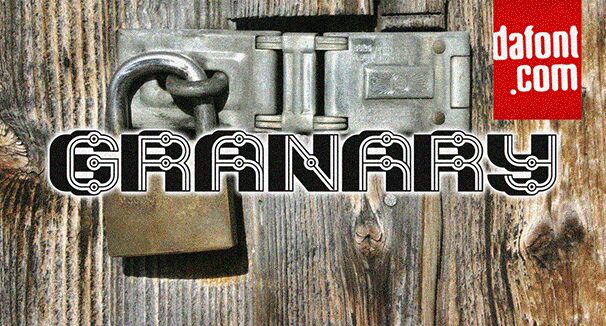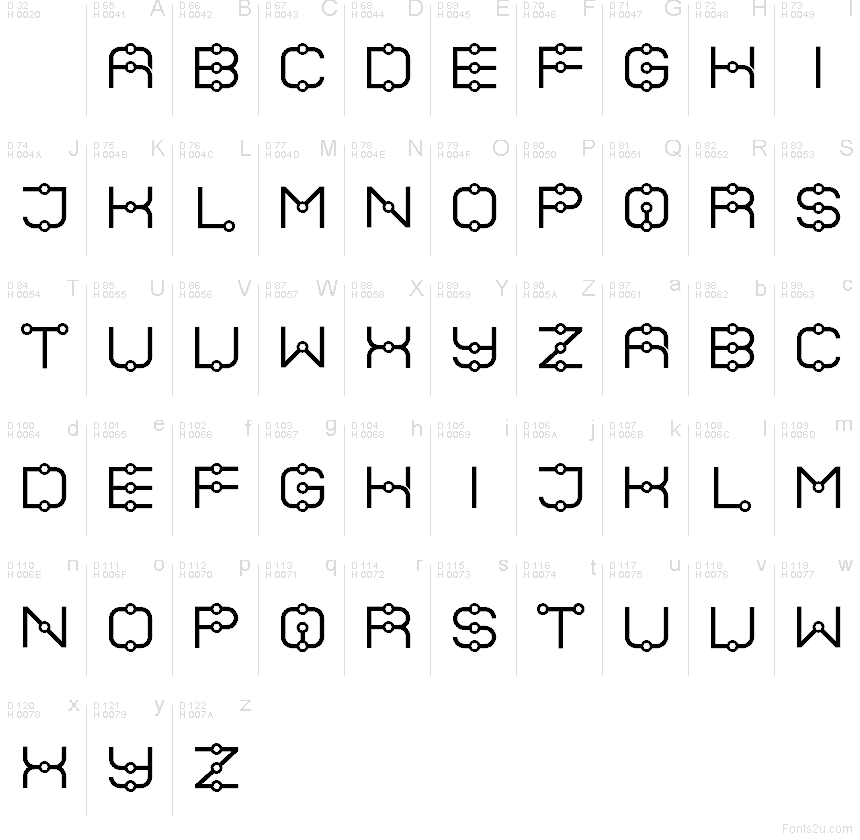
Granary Blues, créée par Vladimir Nikolic, est une police Art Déco gratuite, composée de courbes monolinéaires fluides et d'angles droits nets. Les jonctions circulaires ponctuent les majuscules comme des rivets ou des perles, offrant un rythme ludique et structuré, imprégné d'un style moderniste.
Idéale pour les affiches musicales, les pochettes d'albums, l'identité visuelle de bars, le packaging, les titres courts et les monogrammes qui nécessitent une touche audacieuse d'époque, cette police gratuite se distingue par son caractère unique. Sa construction ouverte et ses détails circulaires récurrents conviennent parfaitement aux textes courts, où ces cercles répétés deviennent un élément fort de la composition.
Granary Blues